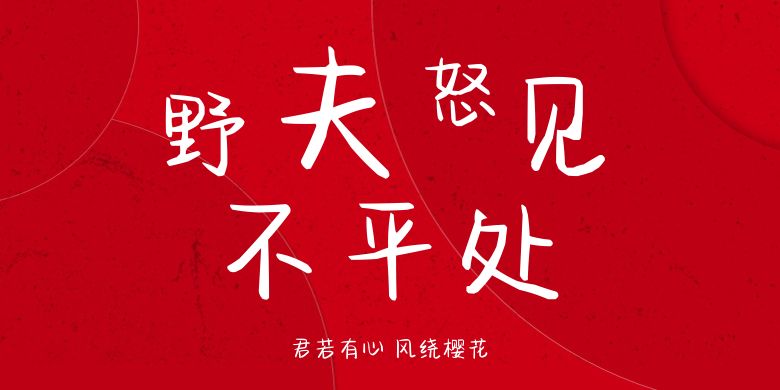
君若有心 风绕樱花
君若有心 风绕樱花,这款字体结构工整、笔画清晰,兼顾美观与易读性,适用于标题、正文、海报、包装、LOGO 等多种场景。字形优雅稳定,风格百搭耐看,适配日常排版与创意设计,让文字呈现更舒适、更具质感。君若有心 风绕樱花一笔一画,皆是细节,以均衡的比例、流畅的线条打造舒适视觉体验,字形端正大气,风格简约现代。无论是商业设计、品牌宣传还是日常排版,都能轻松驾驭,让文字更有格调与力量。君若有心 风绕樱花字体下载。